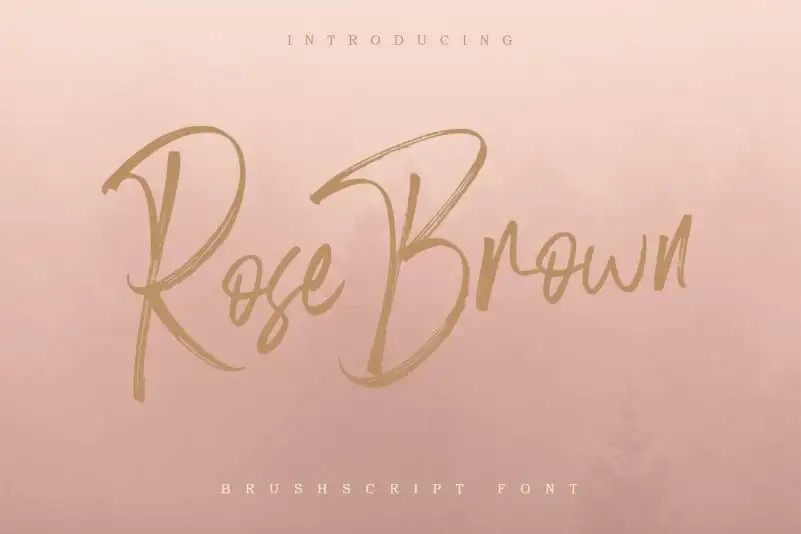
Rose Brown Brush Font – Fonte Grátis
Rose Brown Brush Font
A Rose Brown Brush Font é uma escolha perfeita para quem busca estilos únicos e modernos no seu próximo projeto visual. Essa elegante tipografia escrita a mão incorpora um toque autêntico, tornando-a perfeita para qualquer design em que seja usada. A criação deste tipo de fonte é atribuída ao talentoso designer Youthlabs. A Rose Brown Brush Font vem com linhas naturais e suaves, mas também apresenta a textura característica do uso de uma esfinciona na escrita. Suave para logotipos e materiais de identidade visual, ideal para aplicações como panfletos, medalhões, capas de livros, camisas personalizadas, embalagens e muito mais. Com sua capacidade versátil, a Rose Brown Brush Font se adapta perfeitamente a uma variedade imensa de usos. Seja em um projeto editorial ou na arte de t-shirt, esta fonte oferece um toque único que vai lhe dar aquela pequena diferença no design. Composto por linhas naturais e suaves, ela traz o seu próprio estilo inconfundível para qualquer design.